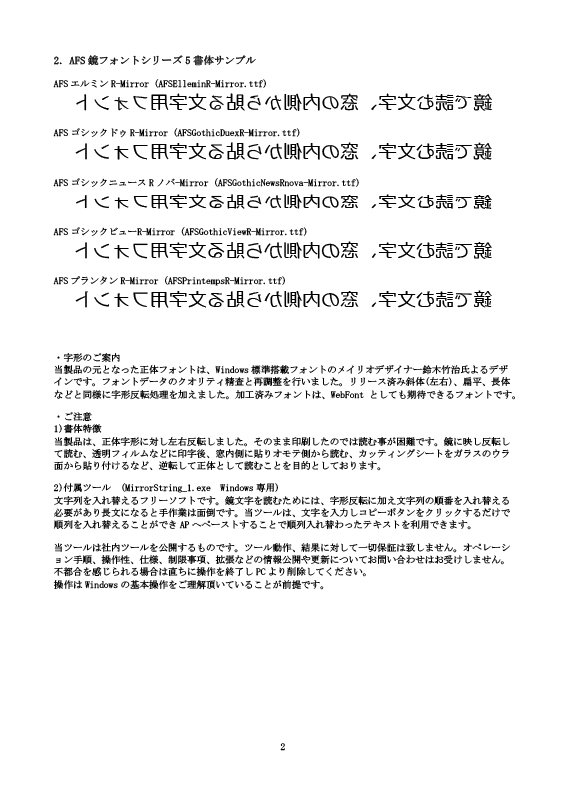
AFS鏡フォント5は左右反転フォント5書体セットです。
テキストエディタなど反転機能を持たないツールやAPでも簡単に鏡文字を印刷出来るようになります。
※プレビューフォントは「AFS エルミンR-Mirror」です。
1.用途
1) 鏡を利用する場所(理容室/美容師)での張り紙など告知文用
2) 窓やドアのガラス面、内側より透明シール貼り付け
3) カッティングシート
4) スマホ自撮りのバックドキュメント
特に店舗窓での利用は、従来外側からの貼り付けでは風雨による劣化があるため、鏡文字によるプリント後の内側貼付での耐用に期待が持てます。